低劣手写体
“字库、字帖”当休矣
近来,大量丑书、手写江湖体进了字库,被央视等权威传媒与大众传媒所采纳,运用到影视字幕、线上网络字体、广告物品等众多方面,甚至被制成软字帖,受众危害面波及广大中小学生在内的社会各界。
著名画家吴冠中说:文盲不可怕,美盲才可怕。今天中国的文盲不多了,但是美盲却很多(包括企业家、媒体人、白领等许多领域的成功人士)。木心先生也曾说:“没有审美力是绝症,知识也解救不了”。权威传媒等广泛使用低劣手写字库,学生描摹低劣字帖则说明国家有关部门缺乏应有的把关措施与有效的管理。一言一蔽之,都是缺乏审美力惹得祸——即以前书法美育的缺失,造成了字库手写者的眼手俱低、字库审定者以及广大受众没有审美力。
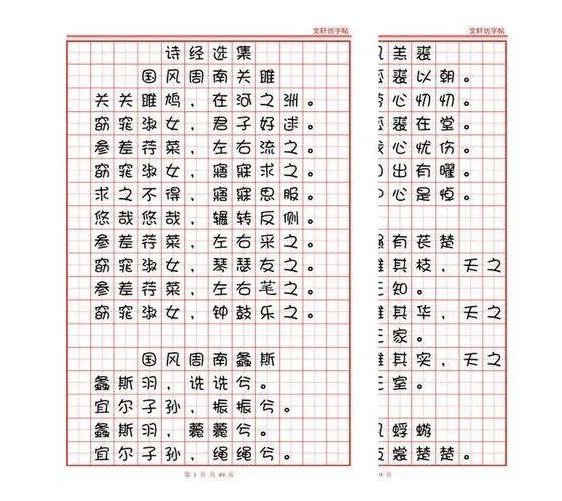
那么,如何能有一双慧眼,识别丑书、江湖体字库、字帖呢?有一个简便的方法。首先看笔法。笔法是书艺的第一要素。凡是“任笔为体,聚墨成形”者,一般而论不是丑书就是江湖体。笔法当“翰不虚动,下必有由。一画之间,变起伏与锋杪(miao);一点之内,殊衂(yu)挫于毫芒”(唐孙过庭《书谱》)。其次看结构。凡是过度夸张不和谐、肆意搞怪炫异者,例如张牙舞爪、故作抖颤、粗糙狂乱......往往非丑即俗。以此二者观之当今“流行”的丑书、江湖体字库,真是“照妖镜下俱现原形”。
孙过庭《书谱》
实用与审美,始终是汉字(含书法)两条并行不悖的脉络。手写体字库是由书法与电脑设计共同完成的。二者的关系既是以书法为体,以设计为用:手写体符合文字规范,其视觉效果形神兼备,再加上电脑技术设计排版,根据需要可适度夸张变形,最终达到和谐统一,形成富有张力富有个性的手写体。
舒同体、启功体即手写体字库的典范。根据新时代实用与审美的多元化需求,手写体字库不能老是司空见惯的舒体、启体,理应不断出新。但出新的前提必是审美价值和实用价值的统一。如果手写体只具有欣赏性而无通用性、可辨识度等等实用性因素是不行的。反之,如果只具有实用性因素而缺乏审美要素,更是行不通的。
王義之题卫夫人《笔阵图》后有言:“若平直相似,状如算子,上下方整,前后齐平,便不是书”即是说缺乏结构美不足以称其为书法,当然不能进入字库,同时也不能制成字帖。而那些为追求所谓“创意”“陌生感”而肆意变乱笔法、字形结构者更不可入库、成帖。否则贻笑大方,大大加剧负面影响。
大约十多年前,曾有计算机公司方面的专家找到笔者说,你的字很漂亮,各种题都会写,写一套书法字体怎么样,我们打算制成字库。笔者以自我风格不成熟为由婉拒之。因为依笔者愚见:手写体入库,广而宣之、广而用之不是件小事儿,字美而规范、做到艺术性与实用性的完美结合,须有坚实的文字学功力与成熟的书法个性与风格,要想高度成熟没有几十年的历练往往难以成就。
虽然新手写体字库需求前景广阔,新字帖需求日益迫切,但是市场建立字库、制作字帖切莫“病急乱投医”,被某些耍江湖的蒙骗过关,或是被某些年轻书手的“勤苦”感动不已而选其丑书、江湖体入库、成帖,毕竟有着坚实的文字学功力的优秀书家并不鲜见,也不难接触。
在当下教育部大力推进“书法进课堂”大趋势大背景下,切实提高学生审美力免受低劣字库、字帖的不良影响是当务之急。在中国书协“书法进万家”等活动中,大力推动书法美育的普及必将惠及普罗大众,使字库审定者、建立者,字帖书写者、印制者具有审美力是重中之重。也许在不久的将来,这些低劣字库、字帖的编写与发行者即感自惭形秽。而在全民基本具有审美力之时,那些低劣的丑书、江湖体字库字帖,自然无人问津、“寿终正寝”了。